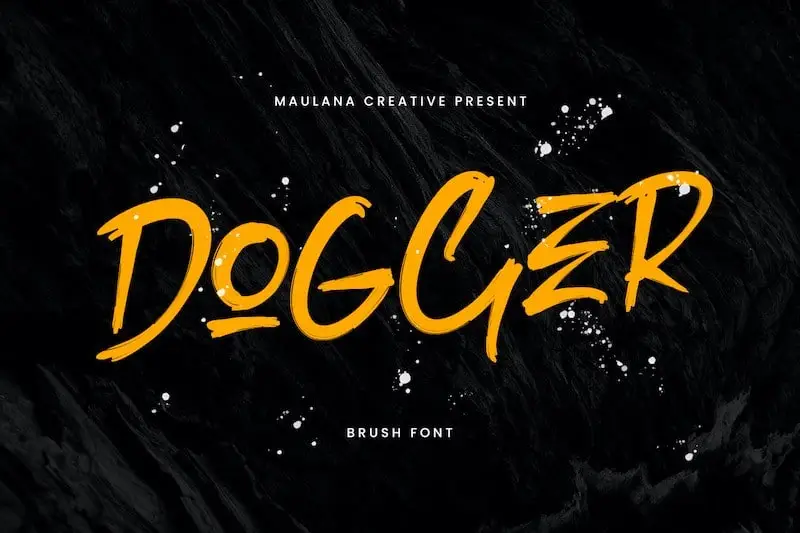
A Dogger Brush Font é uma tipografia feita a mão que se destaca por seu estilo suave e vibrante. Criada pela Maulana Creative, esta fonte foi desenvolvida usando um traço de esmaleta expresso, mantendo detalhes importantes para criar uma combinação chamativa entre letras maiúsculas e minúsculas em alto-peso. Além disso, a fonte inclui alternativas e swashes, permitindo ainda mais personalização dos textos. Ideal tanto para uso em design gráfico quanto em publicidade, a Dogger Brush é uma escolha perfeita para quem busca um estilo único que chama atenção. Se você está procurando por uma fonte de esmalte realista ou deslumbrante que destaque seu trabalho, essa será uma ótima opção. Com sua combinação única entre letras maiúsculas e minúsculas em alto-peso, alternativas e swashes, a Dogger Brush Font é uma ferramenta indispensável para qualquer designer gráfico.